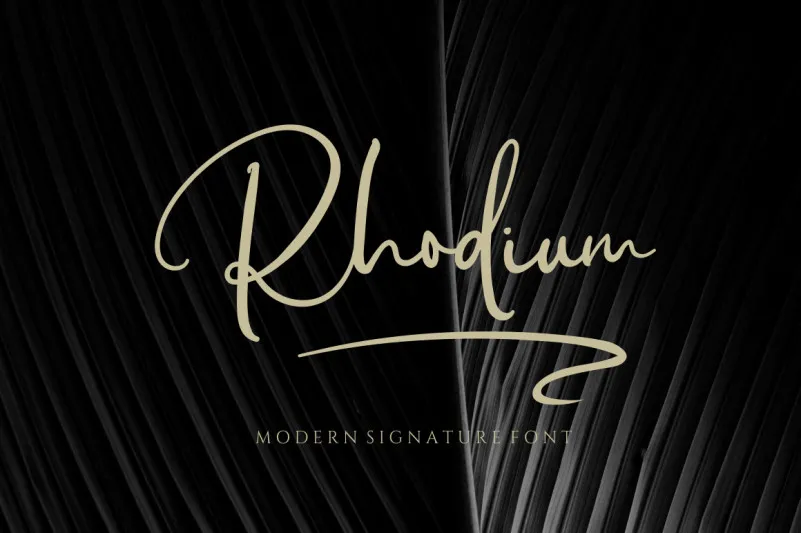
A fonte Rhodium é perfeitamente adaptada para ambientes elegantes e sofisticados. Desenvolvida pelo designer ReyreyBlue, ela transmite uma sensação aconchegante de escrita livre e sofisticação, combinando características manuscritas com um acabamento bem cuidado que se adapta perfeitamente aos projetos mais elaborados. Suas linhas elegantes e fluidas são ideal para estilos de marca elegantes, cartões de convite agradáveis, embalagens sofisticadas, designs de logotipo e, naturalmente, invocando sentimentos românticos nas invitations de casamento. Com seu formato de escrita livre e sua consistência elegante, Rhodium atende às necessidades de designers que buscam um recurso gráfico único para criar projetos atraentes que destacam ao mesmo tempo a qualidade do design e o toque pessoal da mão humana.